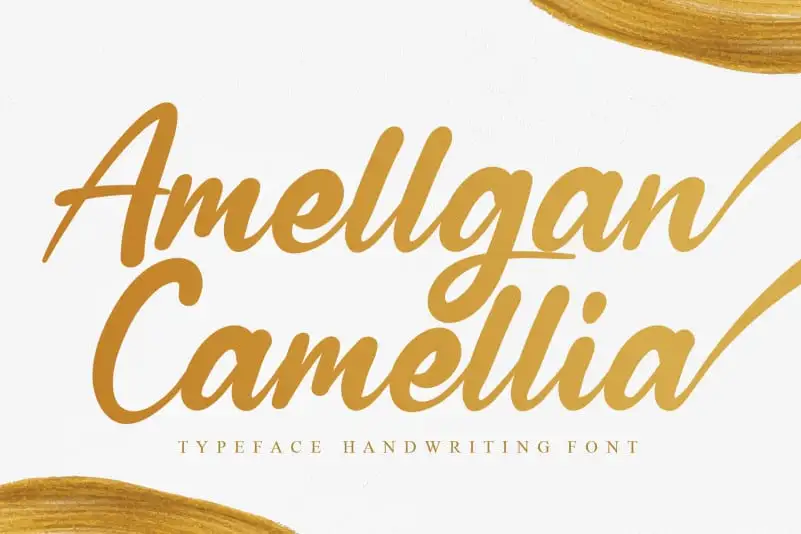
Amellgan Camellia Script Font – Download Grátis
Amellgan Camellia Script Font é uma fonte escrita à mão perfeita para os amantes do estilo delicado e sofisticado. Esta fonte foi criada pelo talentoso designer andikastudio e oferece um toque de criatividade única em cada letra, tornando-a ideal para designers gráficos que buscam dar uma sensação especial às suas criações digitais. Suas linhas elegantes e traços delicados proporcionam um aspecto retrô ao seu design sem comprometer a clareza dos caracteres. É perfeito para aplicar em elementos de marca, embalagens de produtos ou qualquer projeto gráfico que busque transmitir elegância através do texto. Com Amellgan Camellia Script Font, cada letra escrita à mão adquire um charme próprio e transforma seu design digital em algo excepcional e memorável.